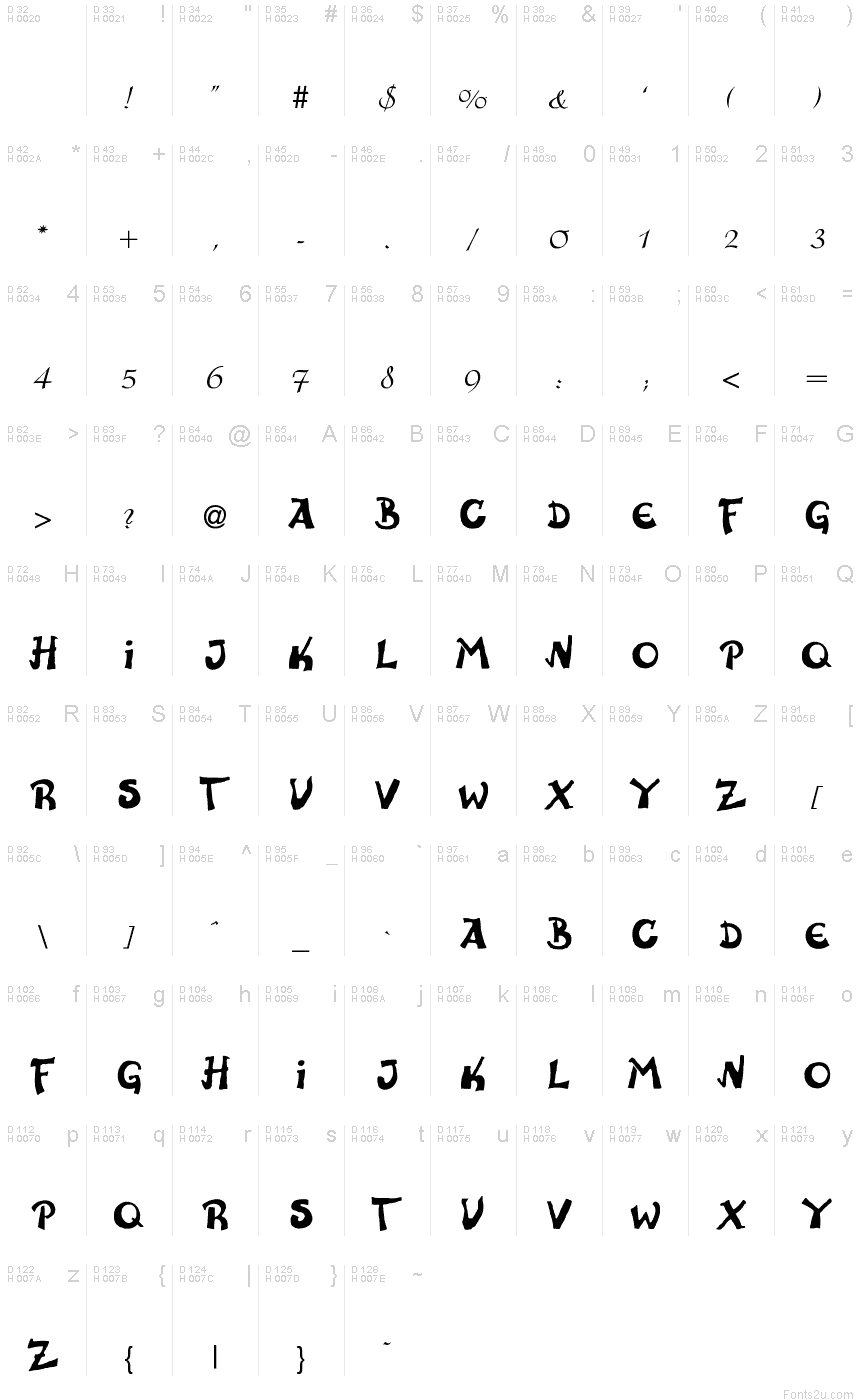
Anatevka Caps
خط Anatevka Caps من Data Becker هو خط عرض كوميدي مجاني يتميز بطابع مسرحي لا لبس فيه. تبدو كل حرف وكأنه مرسوم باليد وبشكل غير متماثل قليلاً، مع ضربات حبر غير متساوية تشعرك وكأنها رُسمت بفرشاة على خلفية مسرحية خشبية. تبرز الأحرف الكبيرة وتلتوي وتميل نحو بعضها البعض، مما يخلق إيقاعاً حياً وريفياً يبعث فوراً في النفس أجواء الحكايات الشعبية وشوارع القرى والقصص القديمة التي تروى تحت أضواء دافئة. إنه يضفي ملمساً وشخصية حيث تبدو الخطوط المحايدة باهتة.
باستخدام Anatevka Caps، لا تكتفي عناوينك بالكلام فحسب، بل إنها تؤدي عرضاً حياً. يتألق هذا الخط المجاني على ملصقات المسرح، وتصاميم أحداث القصص، وهويات المهرجانات الشعبية، وأغلفة الكتب المعبرة، وقوائم الطعام على السبورات في المقاهي، والتغليف الفريد الذي يحتاج إلى لمسة حرفية. استخدمه بحجم كبير للسماح للمنحنيات المرحة والحواف غير المنتظمة بالتنفس، ونسقه مع خط بسيط بلا زوائد للنص الأساسي لتترك لـ Anatevka Caps حرية التعبير عن الدراما.